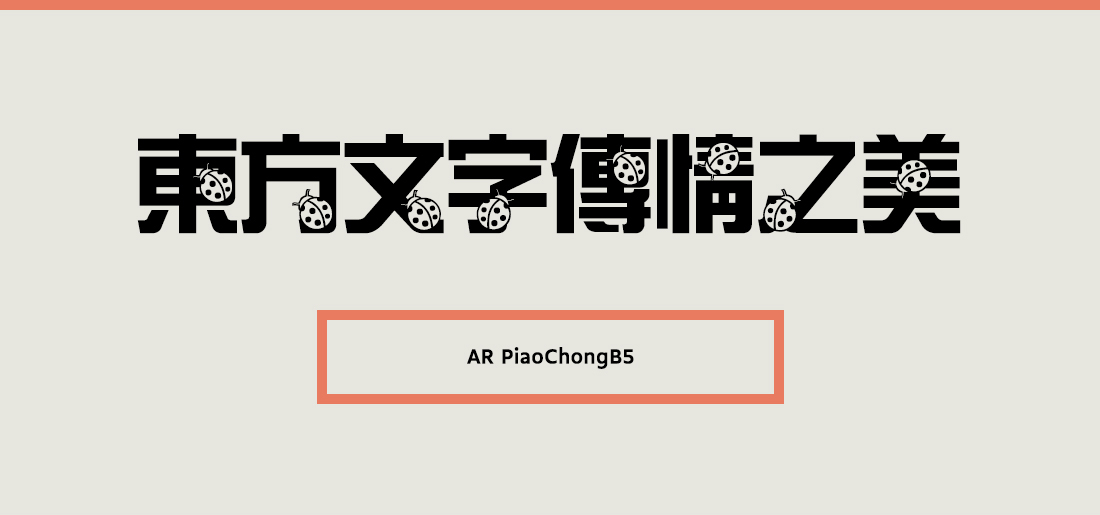
AR PiaoChongB5
PiaoChongB5는 둥근 골격 속에서 직선적인 요소로 인해 힘을 느낄 수 있는 팬시 폰트이다.또한 글립마다 무당벌레 장식을 디자인 요소로 삽입하여 독특한 인상과 재미를 준다.폰트명 뒤에 붙은 B5라는 표기는 번체의 문자코드인 BIG5를 뜻한다. 번체란 중국을 제외한 대만, 홍콩, 마카오 등의 중화권 국가에서 사용하는 전통적인 모양의 한자다. 중국에서 사용하는 간체(GB)와는 달라 잘못 적용할 경우 글립이 제대로 표기되지 않거나 다른 글립으로 표기되는 문제가 발생할 수 있다.